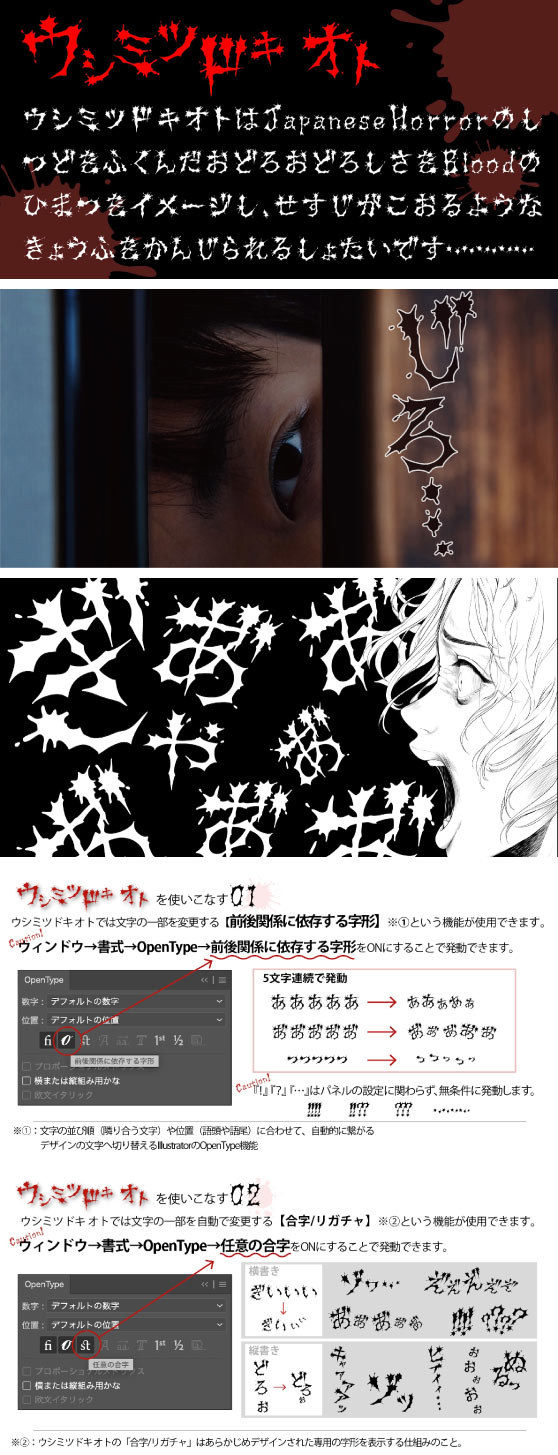
手書き屋本舗 TAw-ウシミツドキオト Kna Regular (Yuko Naito & Yoshimine)
ウシミツドキオトは、ジャパニーズホラーの湿度と血の飛沫を想起させる、背筋が凍る恐怖を表現した書体です。OpenTypeパネルの「前後関係に依存する字形」「任意の合字」を使用し、一部の文字を特殊なデザインへ変化させて使用できます。
ひらがな・カタカナ・アルファベット・数字・記号